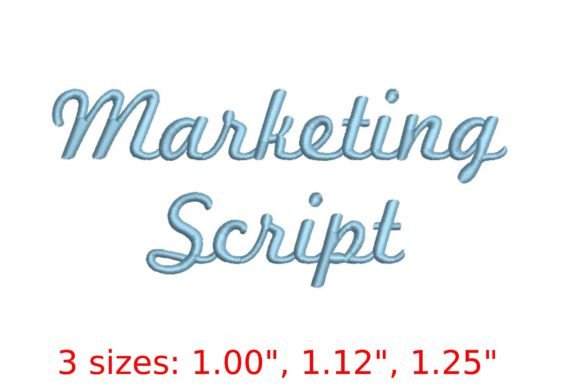
Marketing Script Embroidery Font
Marketing Script Embroidery Font gibi yüksek kaliteli varlıklar arıyorsanız, bu premium paket yaratıcı projeleriniz için harika bir seçimdir.
Hassasiyetle hazırlanan Marketing Script Embroidery Font, temiz vektörler, pürüzsüz tipografi ve içinizin rahat etmesi için ticari bir lisans sağlar.
İster İsteğe Bağlı Baskı (POD) ürünleri, ister düğün davetiyeleri veya sosyal medya grafikleri oluşturuyor olun, Marketing Script Embroidery Font ideal bir uyumdur.